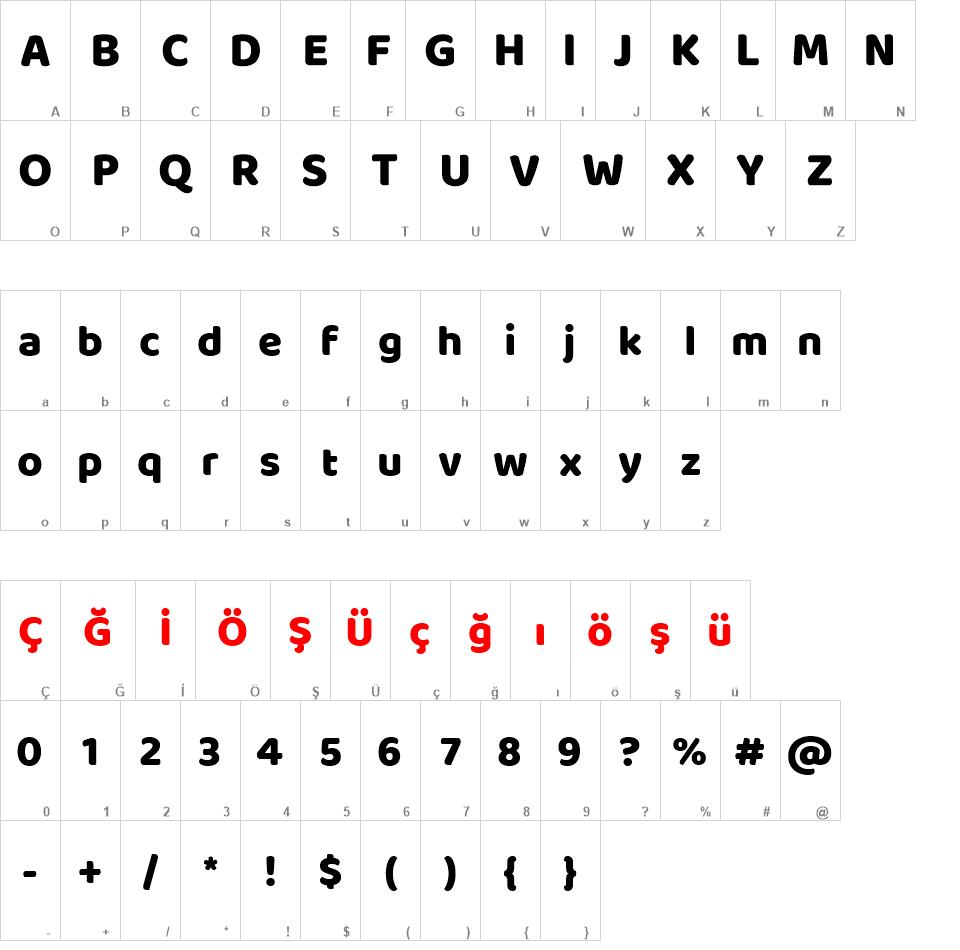
Baloo Bhaina
Baloo Bhaina font
Eine perfekte Mischung aus scharfen Krallen auf dem Boden mit einem Fell Baloo, Typ, ist eine nützliche zusätzliche Display-Schrift. Neun indische Familien auch vorhanden Szenario sowie das lateinische Äquivalent Unicode-kompatibel und wird Pfund lizenziert.
Baloo Schriftarten, verschiedene, mit einem dünnen Ton des Staunens und Nötigste, ist ein schwerer spornloser Entwurf. Rechtschreibung bildet ein paar Skripte in einem einzigen Gewicht zu füllen, die Verwendung von einzelnen und mehreren Skript zu gewährleisten konzentriert sich auf die gleiche Gerechtigkeit auf jede Bewegung dieser Art Forstfragen. Verzweifelte aber zuversichtlich, aber Spaß warm, großzügig und unkompliziert mit Baloo, gibt es Leben alles überall.
In neun Baloo Projekt entwickelt sie Befehl Datei für jede der neun verschiedenen Schriftarten mit einzigartigen lokalen Namen. Jede Schriftart sowie die indische Untergruppe von Latein, Latin Extended und unterstützt Vietnamesisch.
Gut geschrieben und hat die Aufmerksamkeit auf jedes Szenario bezahlt, Baloo, ein Team, bestehend aus einem stabilen Fahrzeugtyp Designer zu verfeinern und zu aktualisieren, wie wir die Schrift lieben. Baloo Devanaga Sarang Kulkarni, Manish Minz und Shuchit Grover, Omkar von Maithili Shingr und Tamil Shanda, Malayalam von Divya Kowshik, Telugu von Supriya Tembe und Noop ist DATY zu, Noop ist DATY durch Gujarat von Kannada, Shuchit Grove von Orija, Bangla von durch Gurmukhs Rajan ist Aadarsh ???? gestaltet. Baloo Latin, ist so konzipiert, durch den Zusatz Typen geteilt werden. Girish und Schrift Engineering Design Unterstützung durch Dalva.